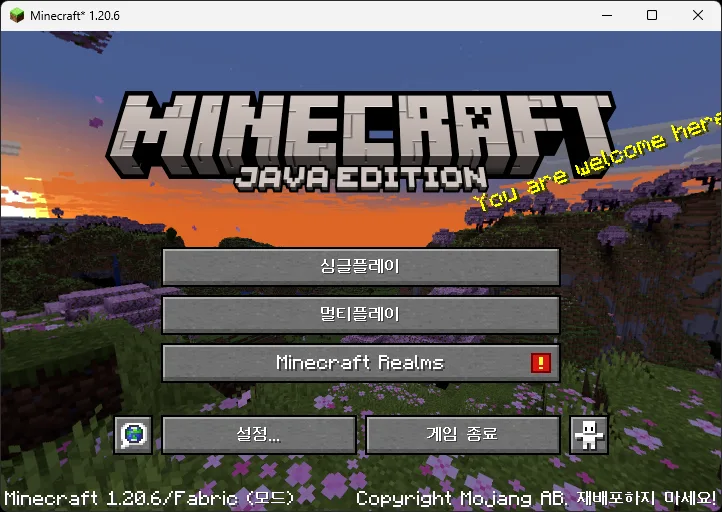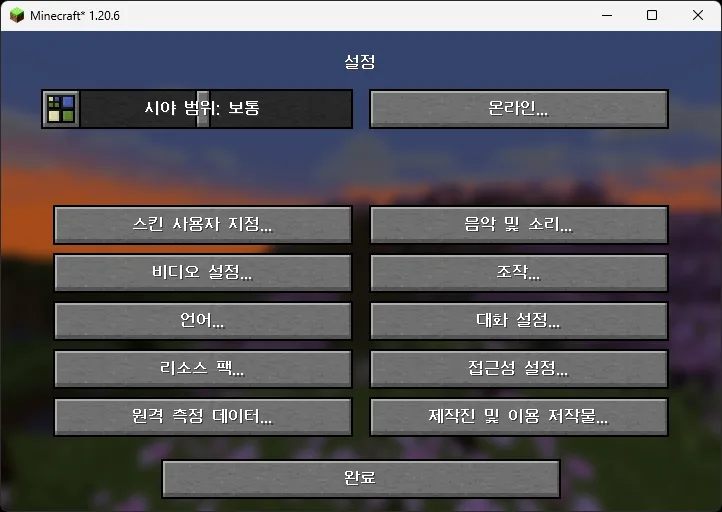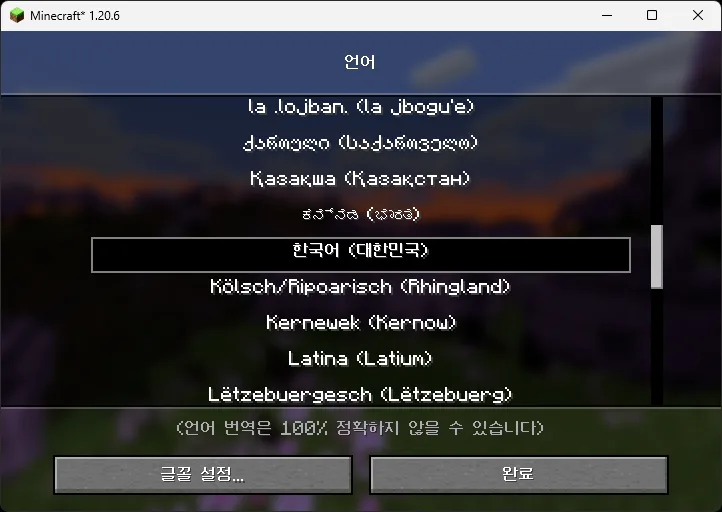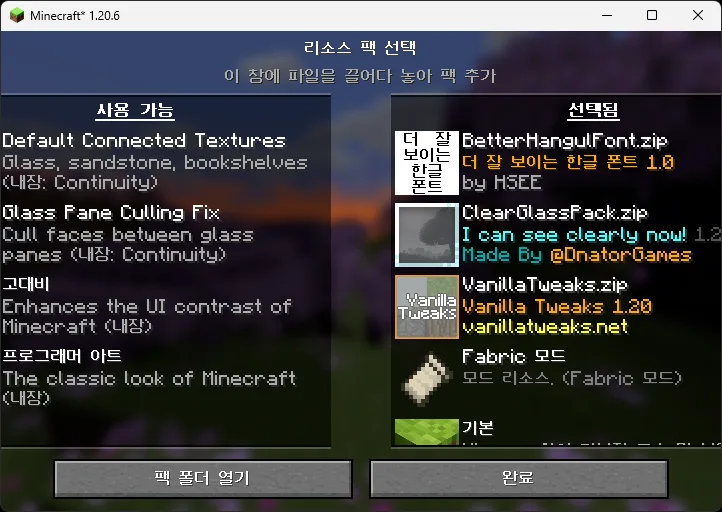
Better Hangul Font
Ресурспак для Minecraft 1.20 и 1.21, улучшающий отображение корейского шрифта хангыль. Включает совместимый ASCII-шрифт для использования с опцией принудительного включения юникода.
Этот ресурспак улучшает визуальное отображение корейского шрифта хангыль в Minecraft версий 1.20 и 1.21. Основное внимание уделено эстетике и читаемости текста.
Пакет включает гармонично подобранный ASCII-шрифт, который автоматически применяется при активации опции принудительного использования юникодного шрифта. Это обеспечивает единообразный стиль отображения всех текстовых элементов в игре.